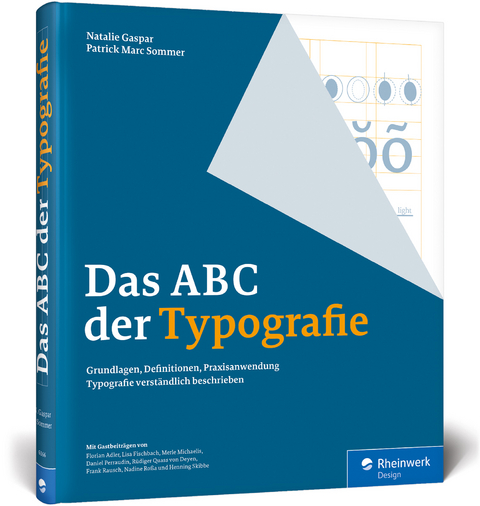
Das ABC der Typografie
Das alles bietet Ihnen das ABC:
- Fachvokabular verständlich erklärt
- Erleben Sie Typografie an Gestaltungsbeispielen
- Intelligent im Doppelseitenprinzip gestaltet
- Zu allen wichtigen Themen: Zeichen, Wort, Zeile, Schriftklassifikationen, Detailtypografie, Schriftwahl und Schriftwirkung
- Schriftgeschichte
- Typografie im großen Ganzen: Typo und Papier, Typo und Farbe, Typo und Bilder, Typo im Layout
- Schrifttechnologie
- Typografie in der digitalen Welt: Webfonts, Grundlagen und Detailtypografie im Web
- Special: Vertiefende Fachbeiträge bekannter Typografen und Designer: Florian Adler, Lisa Fischbach, Merle Michaelis, Daniel Perraudin, Rüdiger Quass von Deyen, Frank Rausch, Nadine Roßa und Henning Skibbe